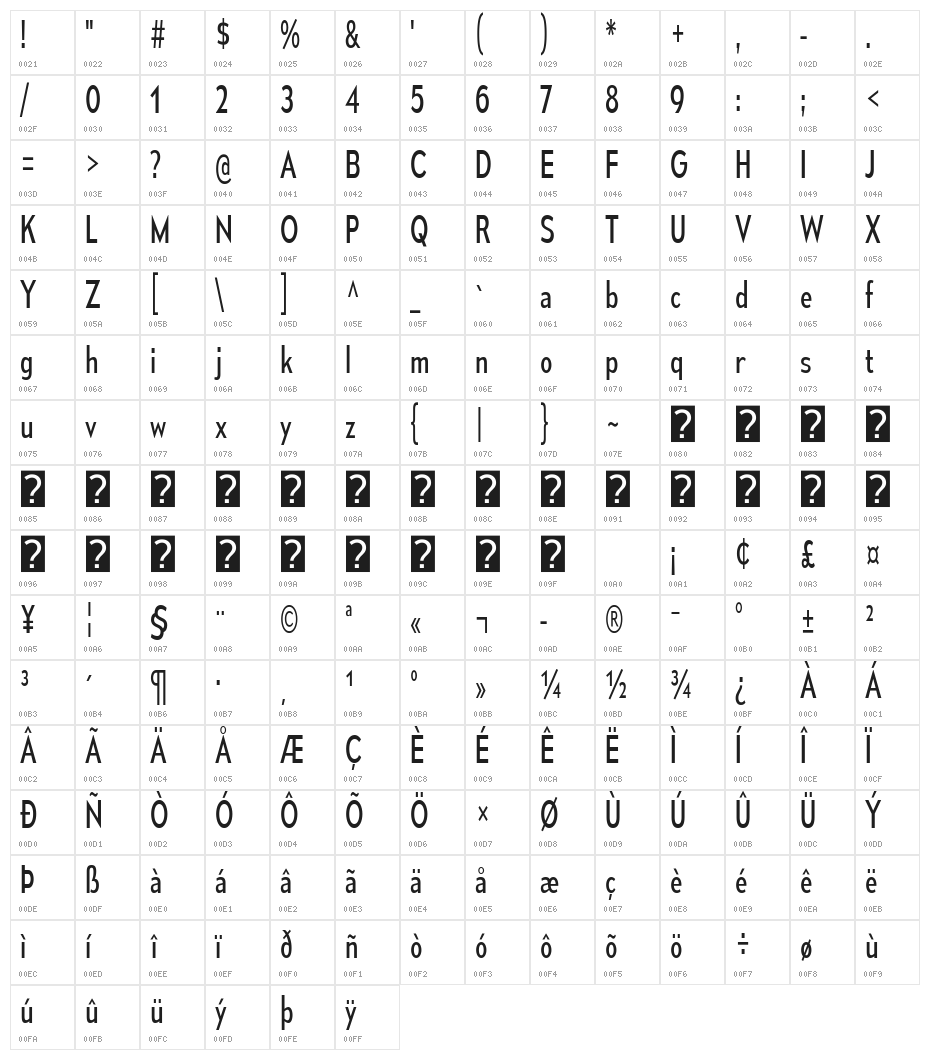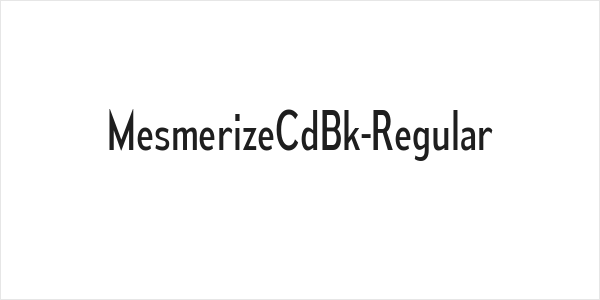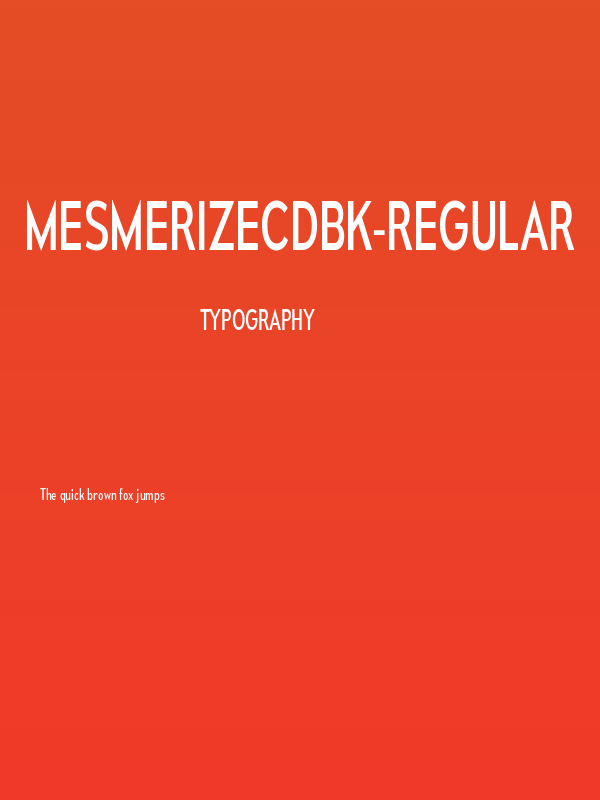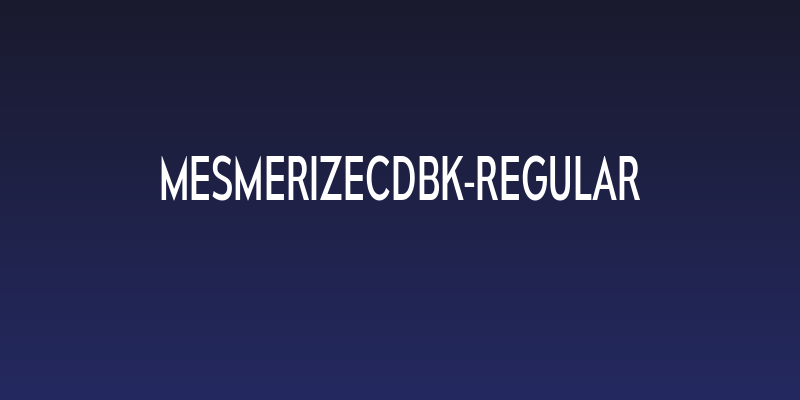
MesmerizeCdBk-Regular Font
| Progetti proposti | Ideal for branding, advertising, web design, and editorial layouts due to its modern and professional appearance. |